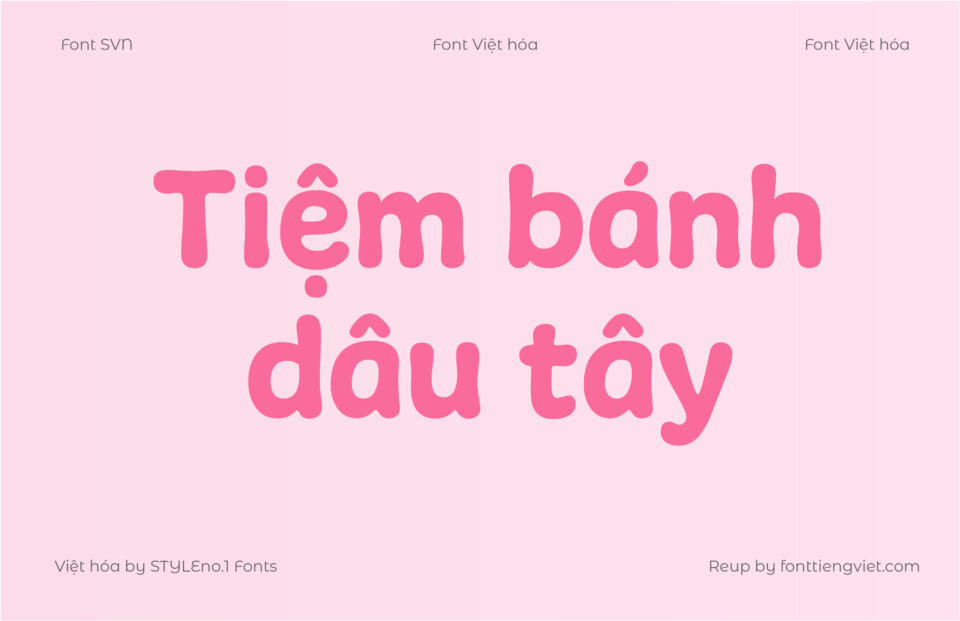
Giới thiệu về Font Việt hóa SVN Freude
Trong thế giới thiết kế đồ họa hiện đại, việc lựa chọn một Font Miễn Phí chất lượng luôn là ưu tiên hàng đầu của các bạn học sinh và giáo viên. Font Việt hóa SVN Freude nổi lên như một lựa chọn hoàn hảo nhờ phong cách thiết kế tròn trịa, vui tươi và tràn đầy năng lượng. Đây là bộ font chữ dạng display mang hơi hướng thủ công, giúp các bài trình chiếu hay báo tường trở nên sinh động và gần gũi hơn với người xem.
Đặc điểm nổi bật của SVN Freude
Bộ font này sở hữu những đường nét uốn lượn mềm mại, loại bỏ đi sự cứng nhắc của các kiểu chữ truyền thống. Khi sử dụng Font Việt hóa SVN Freude, người dùng sẽ cảm nhận được sự phóng khoáng nhưng vẫn đảm bảo tính dễ đọc. Khả năng hiển thị tốt trên cả nền tảng kỹ thuật số và in ấn giúp nó trở thành công cụ đắc lực cho việc làm thiệp chúc mừng, thiết kế bìa sách giáo khoa hoặc các ấn phẩm truyền thông học đường.
Cách ứng dụng Font Việt hóa SVN Freude hiệu quả
Để phát huy tối đa vẻ đẹp của bộ chữ này, bạn nên kết hợp nó với các tông màu tươi sáng hoặc pastel. Font Việt hóa SVN Freude cực kỳ phù hợp cho các tiêu đề ngắn, slogan hoặc những đoạn văn bản cần tạo điểm nhấn thị giác mạnh mẽ. Việc cài đặt font cũng rất đơn giản trên cả Windows và macOS, cho phép bạn sử dụng ngay trong các phần mềm phổ biến như Word, PowerPoint hay Photoshop để phục vụ việc học tập.
Kết luận về bộ font chữ độc đáo
Với sự kết hợp giữa nét vẽ tay nghệ thuật và bộ dấu tiếng Việt chuẩn xác, đây chắc chắn là nguồn tài nguyên quý giá cho cộng đồng yêu thiết kế. Bạn có thể dễ dàng tìm kiếm và tải xuống Font Miễn Phí, Font Việt Hóa, Font Việt hóa SVN Freude để bắt đầu hành trình sáng tạo của mình ngay hôm nay. Hy vọng bộ font này sẽ mang lại cảm hứng mới mẻ cho những dự án sắp tới của bạn.